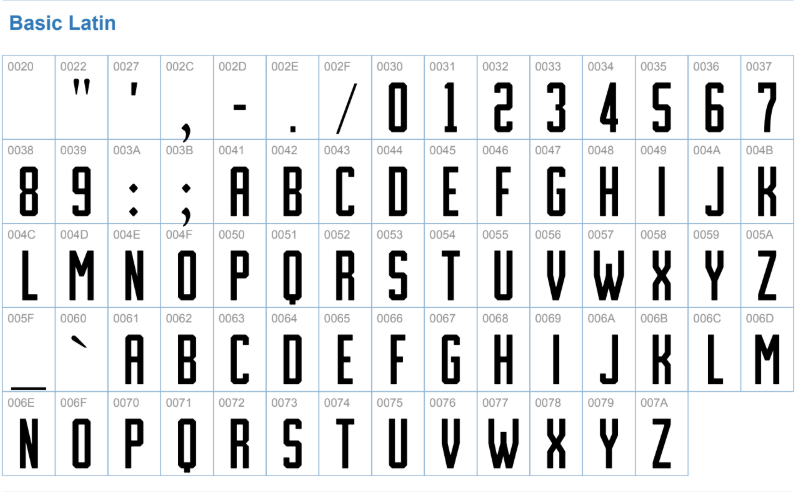
A contagem regressiva para a Copa do Mundo de 2026 já começou, e a seleção da Dinamarca chega com tudo — inclusive na identidade visual. A nova tipografia oficial do time escandinavo para esta temporada traduz com exatidão a alma nórdica: limpa, funcional e com personalidade discreta que grita nas arquibancadas.
Se você é designer, torcedor apaixonado ou cria camisas personalizadas, ter a fonte certa em mãos faz toda a diferença. Ela aparece nos números, nos nomes dos craques e nas peças de comunicação da DBU, virando item obrigatório para projetos gráficos em 2026.
Estilo visual da tipografia
A fonte da Dinamarca 2026 aposta em traços retos e bem definidos, com cantos levemente arredondados que suavizam a leitura sem perder a força visual. Os números têm altura uniforme e espaçamento generoso, pensado para máxima legibilidade nos estádios e nas transmissões em 4K.
O desenho foge do óbvio: moderno sem ser futurista demais, tradicional sem parecer antigo. O filete interno branco nos números cria um contraste elegante com o fundo vermelho, assinatura clássica do estilo escandinavo. Funciona bem em placares, placas de publicidade e, claro, nas costas da camisa.
Aplicação no uniforme
No manto Home, a fonte aparece em branco sobre o vermelho icônico, com aplicação térmica que gruda no tecido sem pesar. O uniforme Away inverte o jogo: tipografia preta ou cinza-chumbo sobre base clara, mantendo a sofisticação. O terceiro uniforme Third, na cor carvão, recebe números em tom prateado metalizado, valorizando a fonte em condições de baixa luz.